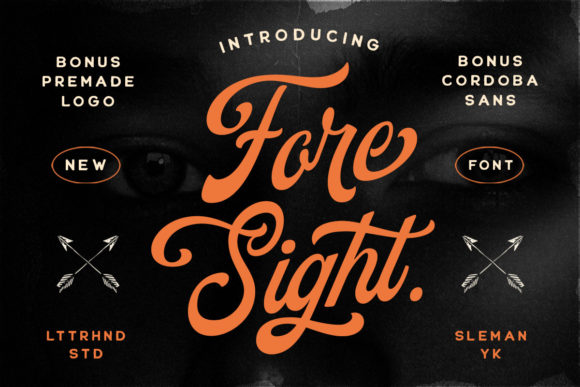
Foresight - это великолепный и смелый дуэтный шрифт (рукописный и шрифтовой), созданный для того, чтобы придать вашим заголовкам и логотипам оттенок ретро. Этот шрифт читается как сильный, уверенный и динамичный.